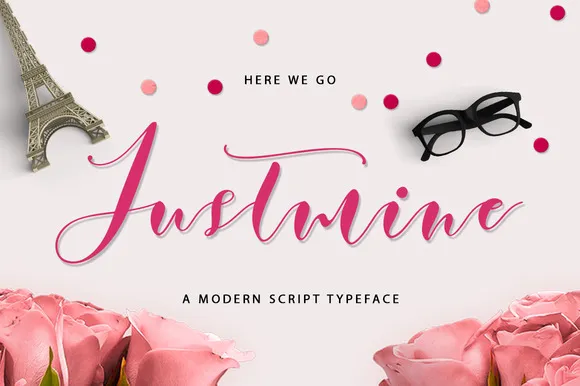
Justmine Script Font
A Justmine Script Font é uma fonte inspirada no entrelaçamento entre a escritura manuscrita e a tipografia moderna. Ela se destaca por sua elegância fluida, oferecendo um estilo moderno e divertido que combina harmoniosamente em projetos como logomarcas, identidades de marca, embalagens de produtos, cartões de convite, e muito mais. Esta fonte vem com uma vasta gama de letras maiúsculas e minúsculas, pontuação completa e numerais que garantem a facilidade de uso necessária para qualquer projeto. Além disso, inclui suporte multilíngue para atender a diferentes demandas linguísticas, juntamente com alternativas criativas e divertidas que adicionam um toque único aos seus trabalhos. Seja você um designer ou criador de conteúdo, Justmine Script Font é perfeita para transformar qualquer projeto em algo realmente especial.